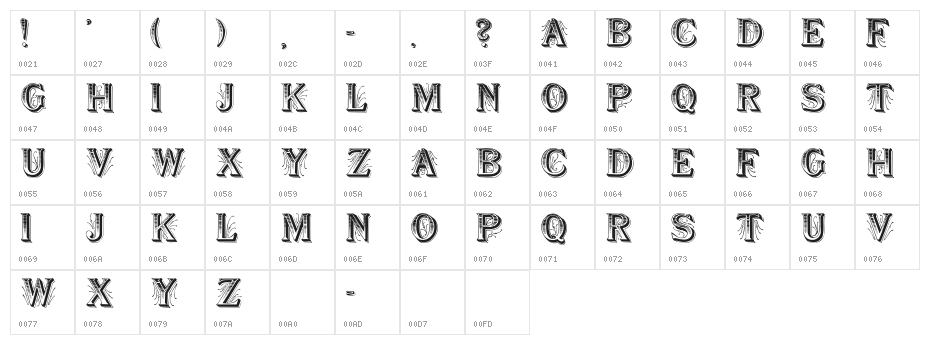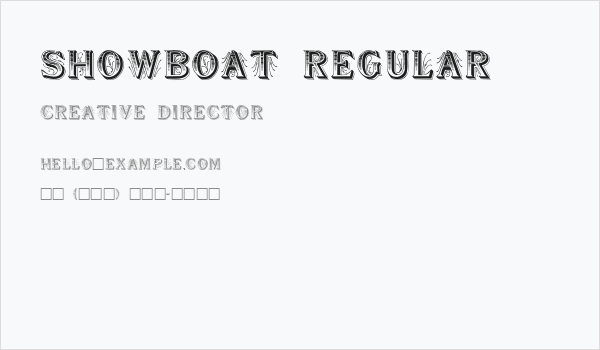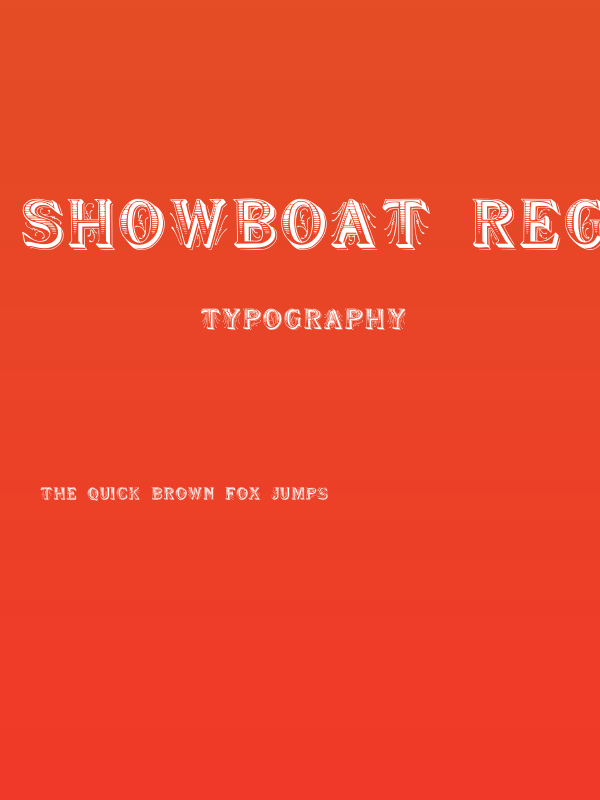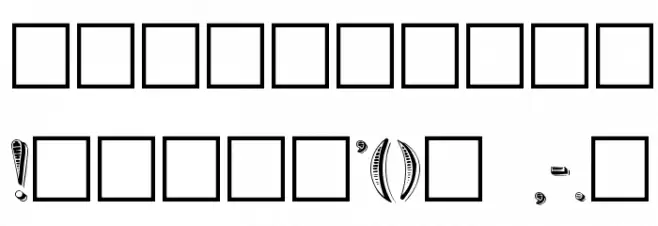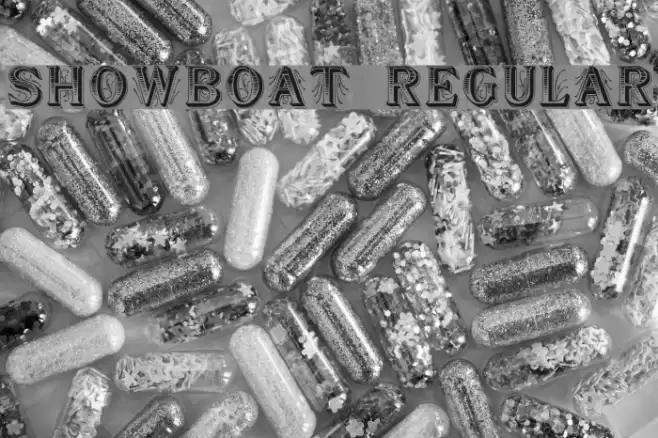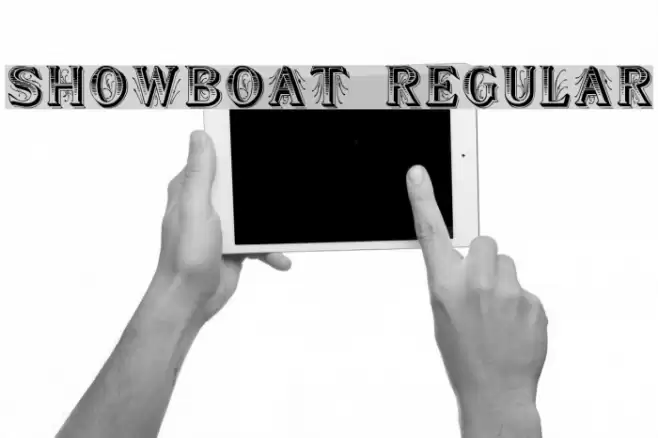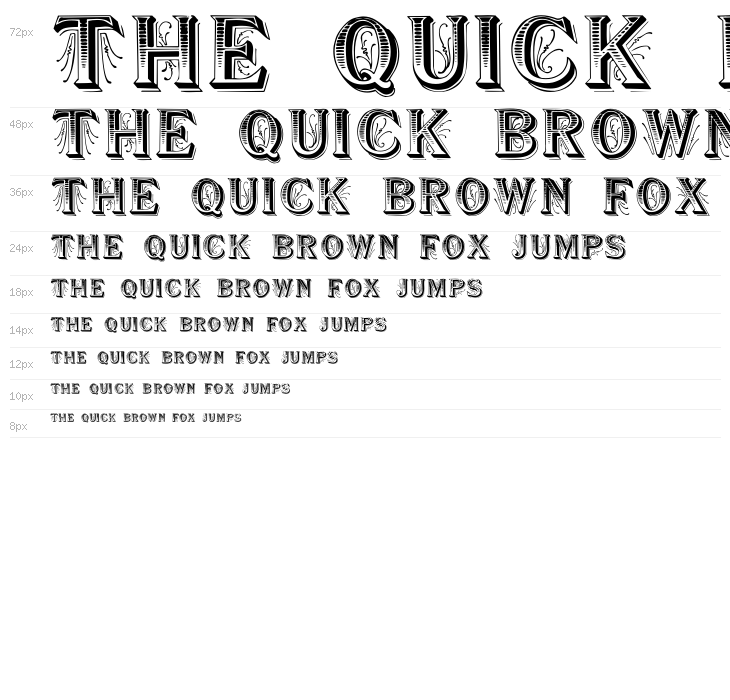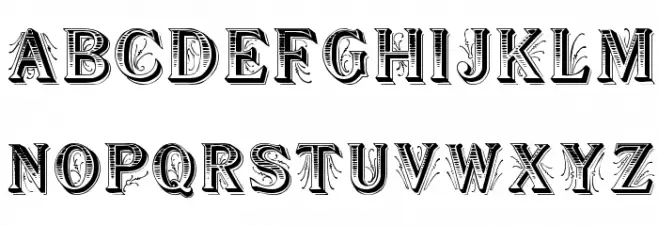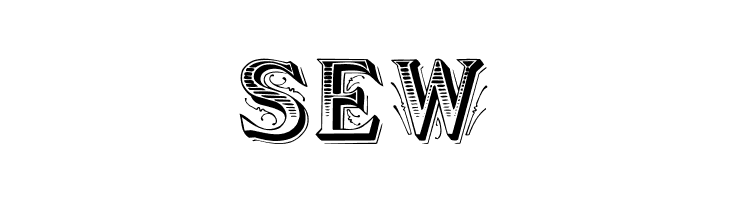
Showboat Regular Font
| Proiecte propuse | Ideal for use in posters, signage, theatrical programs, or any project requiring a vintage or decorative touch. |